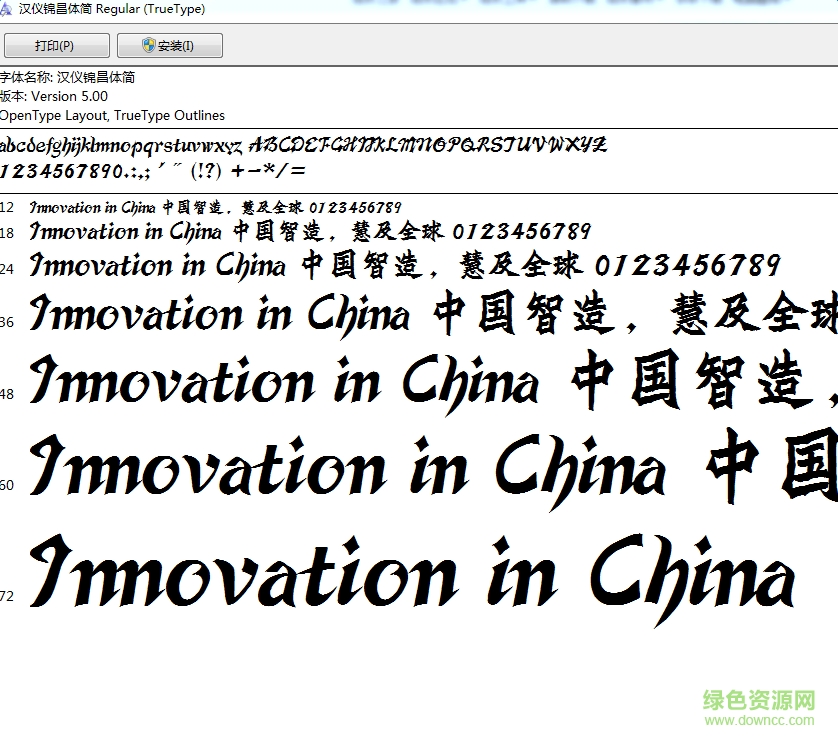
漢儀錦昌體簡字體
漢儀錦昌體簡是一款漢儀類古典文雅風(fēng)格字體軟件,錦昌體一筆一畫一絲不茍,粗細(xì)相間,優(yōu)雅氣息十足,下面即是字體效果預(yù)覽圖,非常好看!還有更多類似好看字體歡迎來綠色資源網(wǎng)下載體驗(yàn)!
漢儀錦昌體簡是一款應(yīng)用于藝術(shù)設(shè)計(jì)方面的簡體中文字體,該字體筆畫粗壯,尾部的甩尾有力且有豐富的筆觸細(xì)節(jié),大字效果突出且引人注目;并且最大程度還原作者書寫字形,細(xì)節(jié)表現(xiàn)完整,且字庫完整,可以廣泛應(yīng)用于名片設(shè)計(jì)、新聞媒體、宣傳海報(bào)、ppt、影視制作以及內(nèi)容用字等領(lǐng)域。
該字體橫細(xì)豎粗,非常的文雅脫俗,整體效果十分酷炫好看,盡顯書法大師的魅力,用來耍酷再合適不過了!